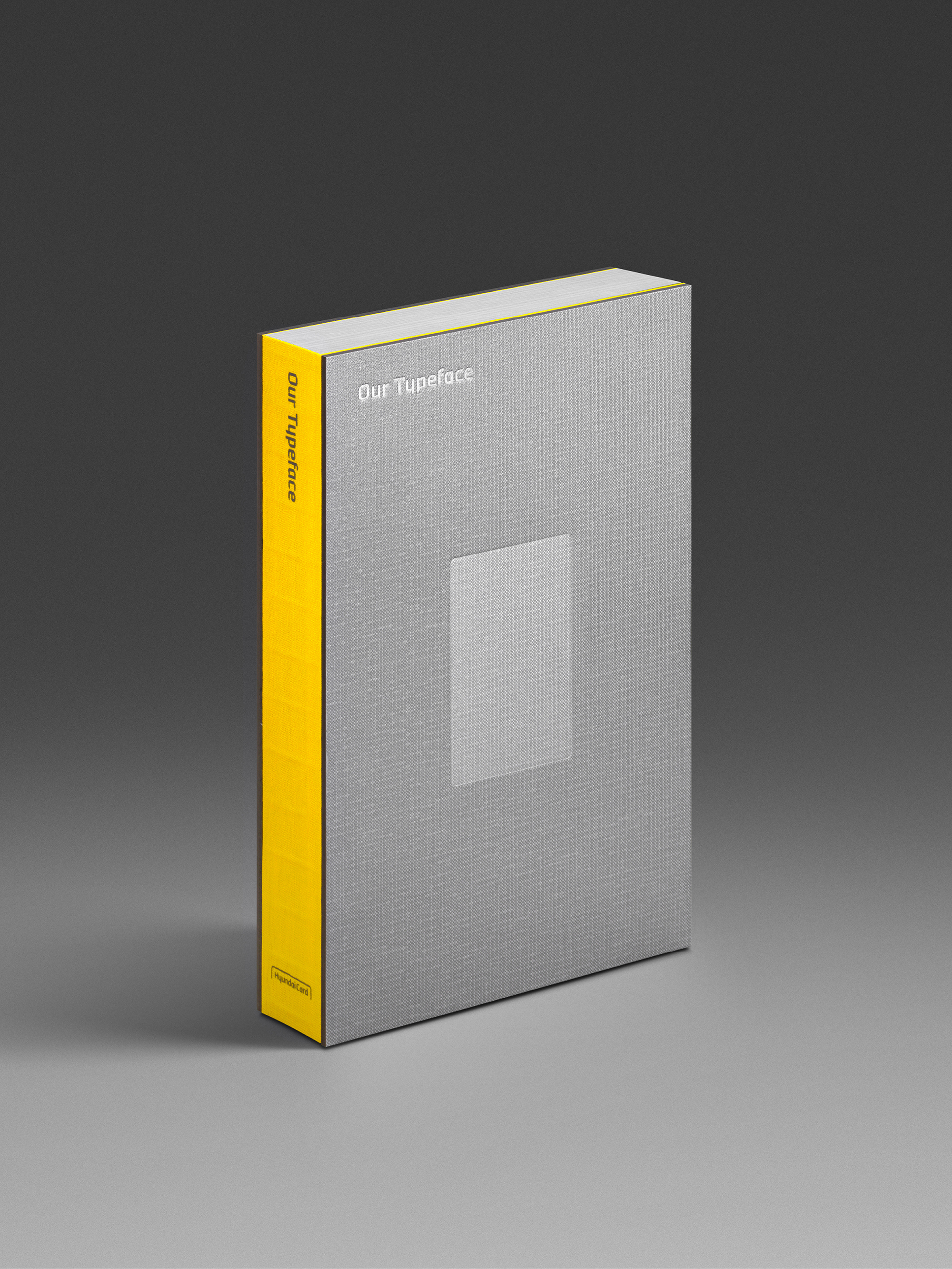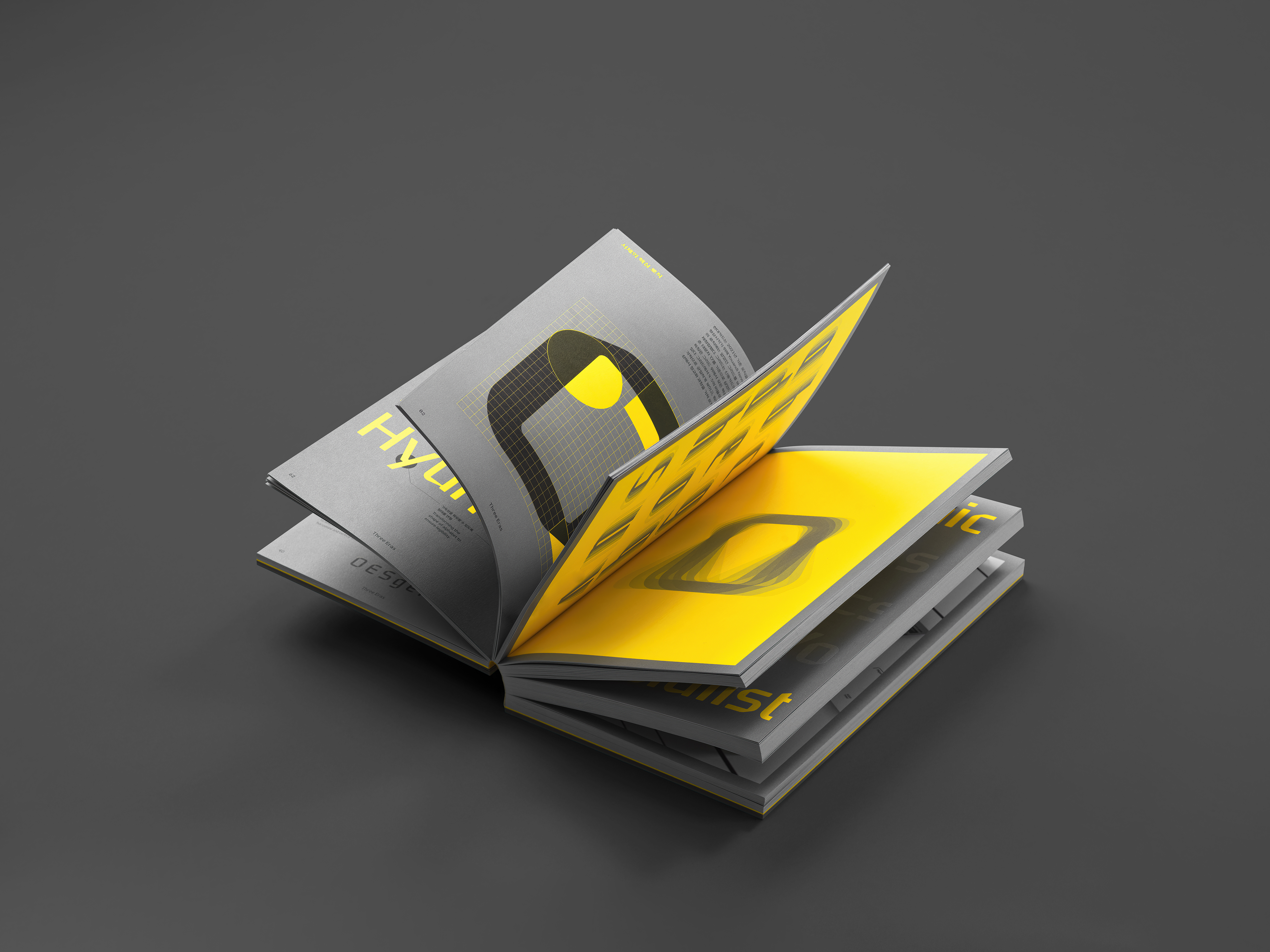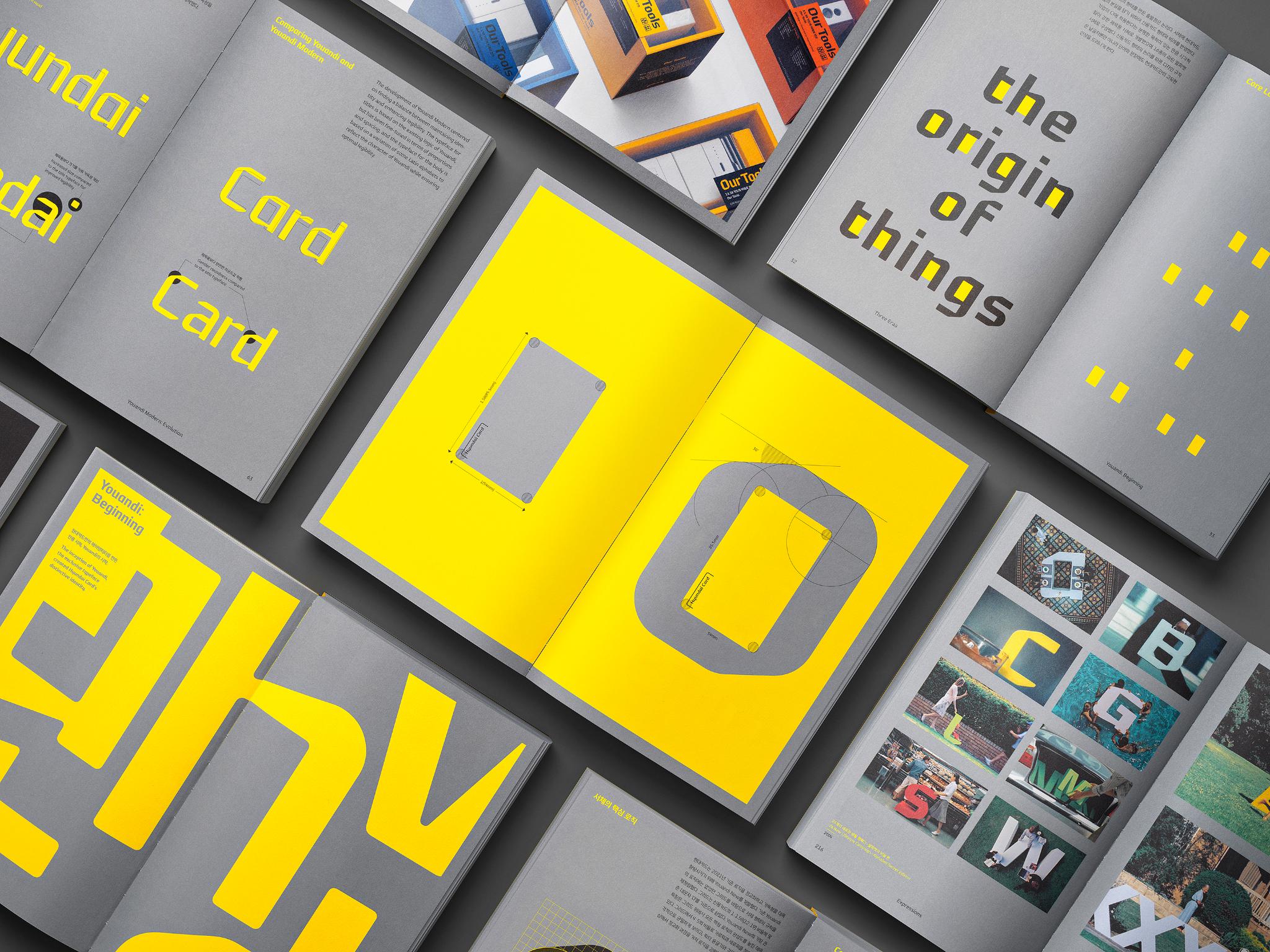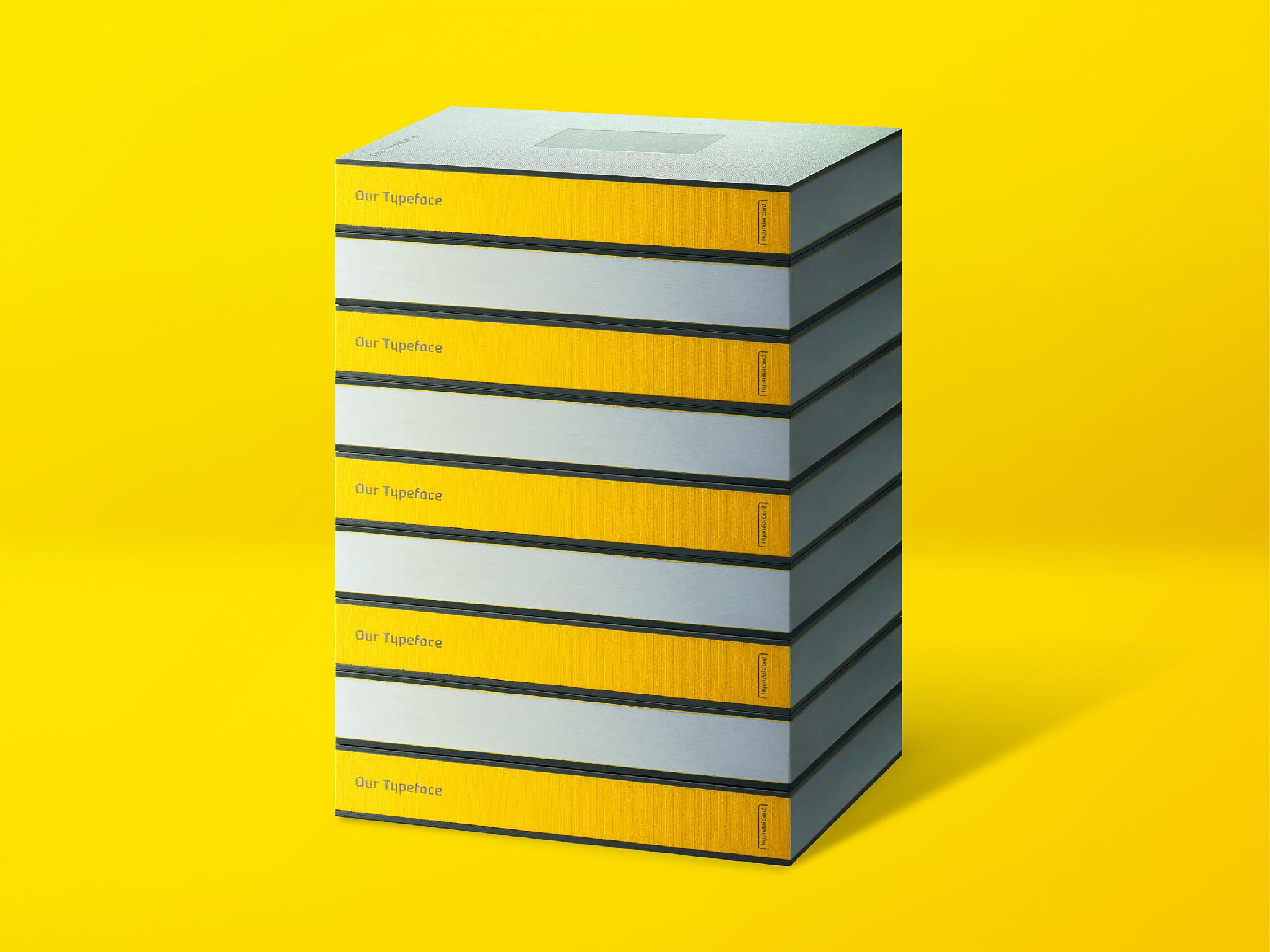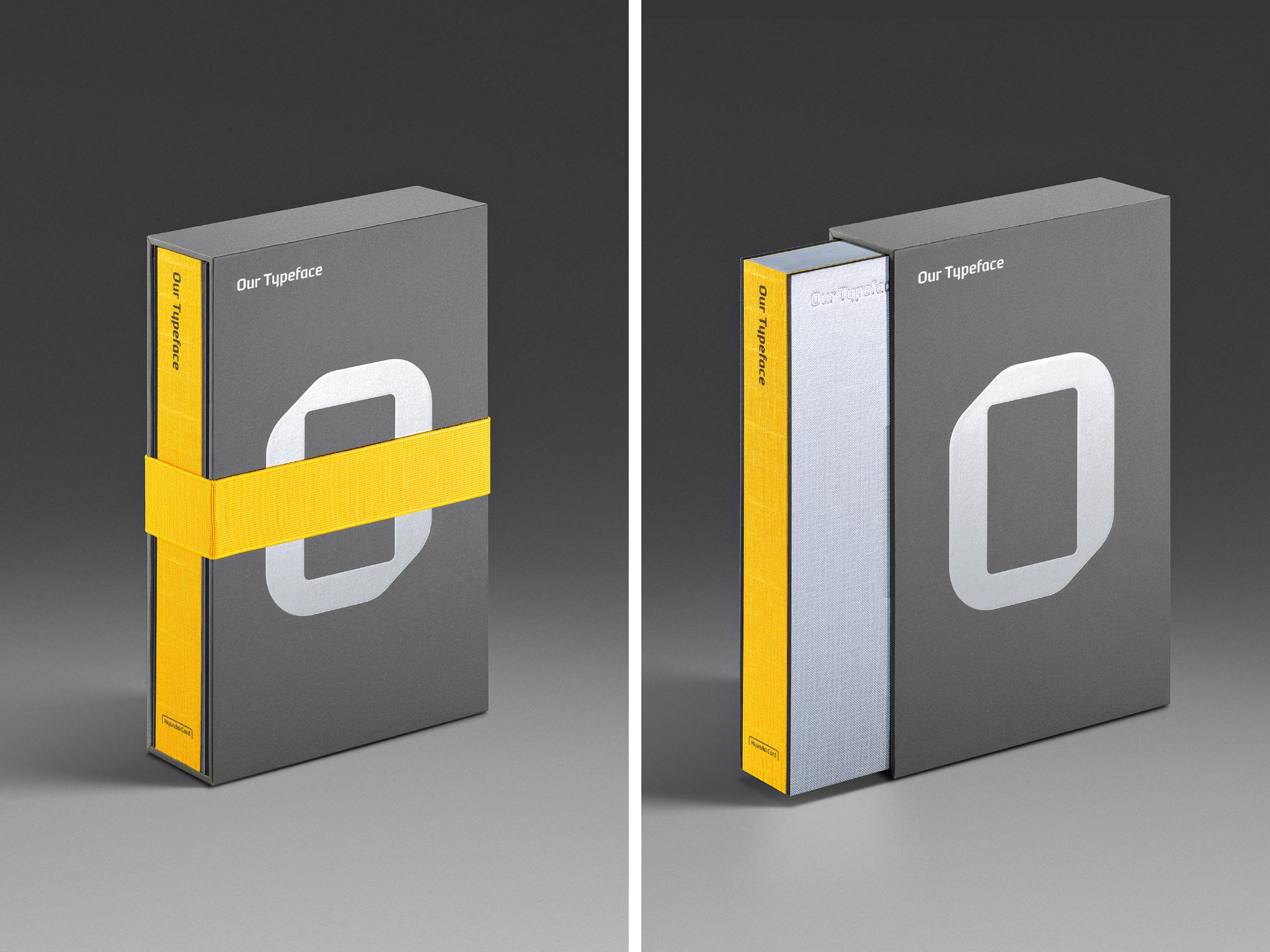
Our Typeface
Hyundai Card
『Our Typeface』は、現代カードの書体「Youandi」の20年にわたる歩みを記念するアーカイブブックです。本書は主に三つのセクションで構成されています: 「三つの時代」:2003年、2012年、2021年に発表された三つのユアンディ書体(ユアンディ、ユアンディモダン、ユアンディニュー)の特徴を紹介する見本帳「思想」:ユアンディを含む企業書体に関する専門家の洞察と考察「表現」:様々な文脈におけるユアンディの応用例を集めたコレクション この明確な構成により、非専門家からデザインプロフェッショナルまで、多様な読者層が企業タイポグラフィとブランディングに触れられるよう設計されている。